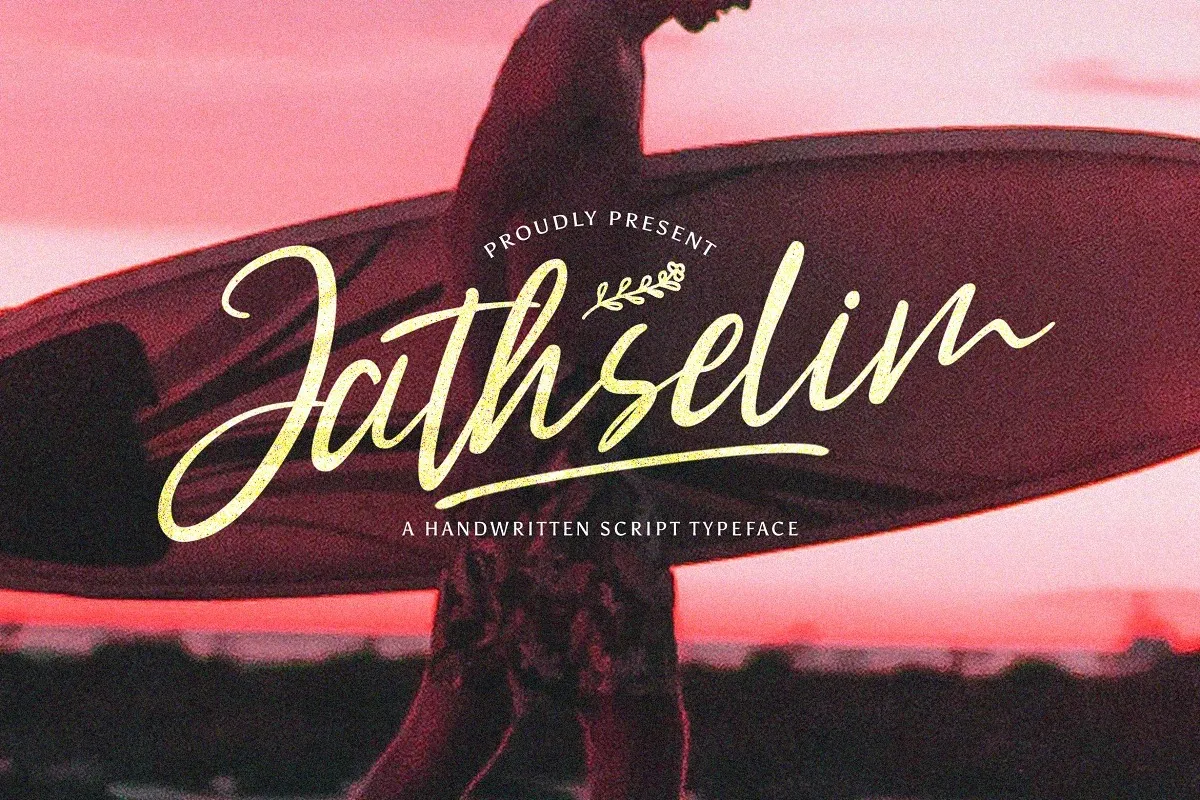
Jathselim Font – Download Grátis
A ‘Jathselim Font’ é uma elegante tipografia script criada pela StringLabs que captura a essência encantadora e descontraída do estilo manual. Seus caracteres vivos parecem dançar ao lado do linha de base, apresentando um equilíbrio perfeito entre beleza e simplicidade. Este tipo de fonte é especialmente adequada para projetos criativos que buscam agradar uma ampla gama de ideias, seja ela em logotipos, selos ou até mesmo designs gráficos mais tradicionais. Sua presença enriquece e rejuvenesce qualquer design, fazendo com que ele se destaque ainda mais. Experimente incorporá-la em seu próximo projeto para explorar o poder criativo desta fonte incrivelmente única.